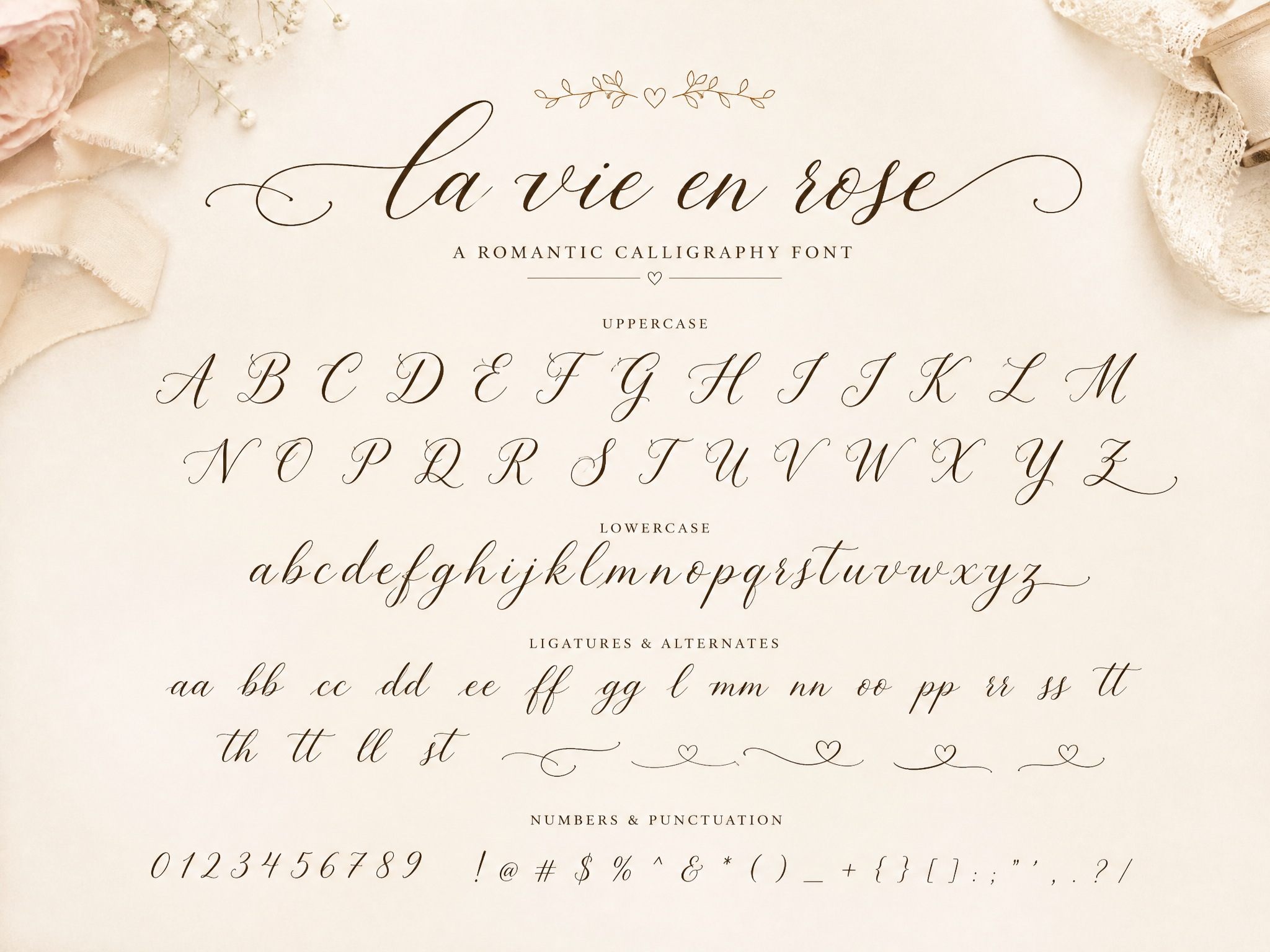
Zarif El Yazısı & Kaligrafi Font Paketi, akıcı bağlantıları ve zarif süslemeleriyle projelerinize sıcak ve kişisel bir dokunuş katar. Düğün davetiyeleri, logo tasarımları, ürün etiketleri ve sosyal medya alıntı görselleri için idealdir. Font; alternatif harf formları, başlangıç ve bitiş süsleri (swash) ile bağlama duyarlı ligatürler içerir. Böylece gerçek bir el yazısı doğallığı yakalarsınız. Türkçe karakterler dahil geniş bir glif desteği sunar. OTF ve TTF formatlarında teslim edilir; ticari kullanıma uygundur. Zarif ve romantik bir estetik arayan tüm tasarımcılar için güçlü bir seçenektir.
Zarif El Yazısı & Kaligrafi Font Paketi